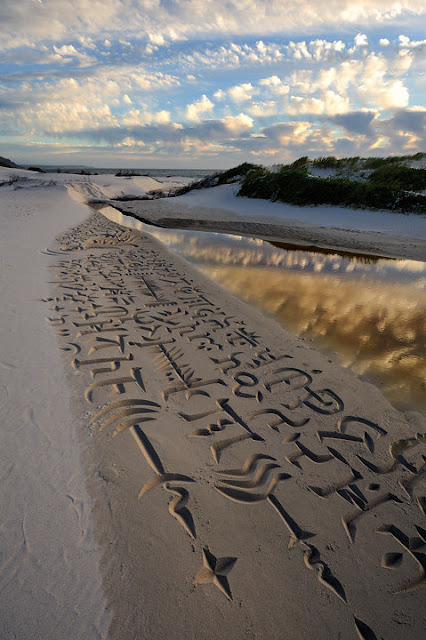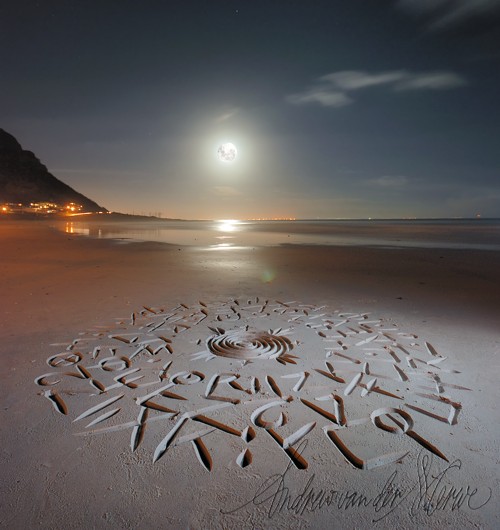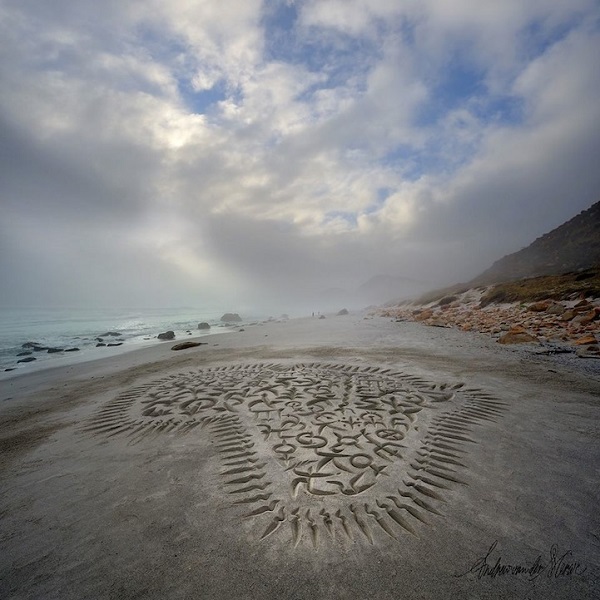
Cuando la tipografía pasa a formar parte de la naturaleza
El diseño gráfico siempre ha ido muy unido al papel, lápices y otros materiales que van más acorde con un espacio de trabajo que con cualquier otra cosa. Sin embargo, a lo largo de los años se ha podido ver que el diseño gráfico puede formar parte de otros escenarios, véase los diseños que vemos en la calle a través de posters o murales o de la naturaleza, creándose tipografías con hortalizas y otros materiales orgánicos.
Ahora el diseño, y más en concreto la tipografía, pueden formar parte de la naturaleza de una forma efímera y muy artística. Andrew van der Merwe, un tipógrafo se ha considerado como el «primer calígrafo de playa«, ya que ha creado unas escrituras muy bonitas en la arena de algunas playas. Su trabajo es descrito como «muy temporal» debido al sentido efímero de las obras. Sus creaciones no duran más de una hora, y poco a poco se las lleva el mar, la brisa y el viento.
Para crear esas obras, el autor utiliza instrumentos especiales y cava en la arena, formando las formas de las letras. Una vez que acaba, realiza fotografías de las obras sin dejar ninguna huella o pisada. Lo más curioso y lo que más nos gusta es que las formas de las letras están inspiradas en los sistemas de escritura africano, pero también de las variaciones que hacía con su mano mientras jugaba en la arena.
Una técnica original, bastante costosa, pero que da unos resultados increíbles donde la tipografía pasa a formar parte de la naturaleza, a través del land art